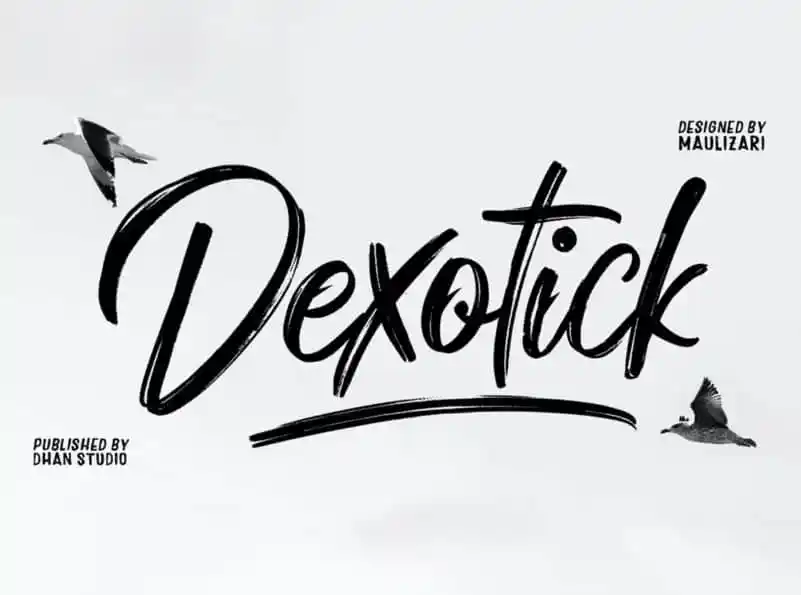
Dexotick Brush Font – Download Grátis
Estou aqui a font Dexotick Brush para quem procura algo único e envolvente para projetos de design. Esta font é um tipo desenhado com uma paleta interessante, especialmente bem adaptada para trabalhos como marcas de marca, logomarca, embalagens de produtos, panfletos, convites, cartões de agradecimento e até mesmo para escrever sobre blogs ou diários pessoais. Além do seu visual chamativo e texturado que faz com que cada letra seja única em sua aparência e se destaque, Dexotick também oferece algumas letras desenhadas manualmente sem conexão. Isso permite que os textos criados tenham um aspecto singular e intrigante. Esse tipo é perfeito para aqueles que valorizam a personalidade nos seus projetos de design. A font Dexotick Brush, em par com seu característico design script, será uma ótima escolha para criar algo que expressa quem você realmente é. Não só é um recurso indispensável no arsenal dos designers digitais, mas também se tornará o ponto focal de qualquer projeto gráfico. Seja para marcas de marca poderosas ou cartões de agradecimento criativos, Dexotick Brush garantirá um design único e memorável.